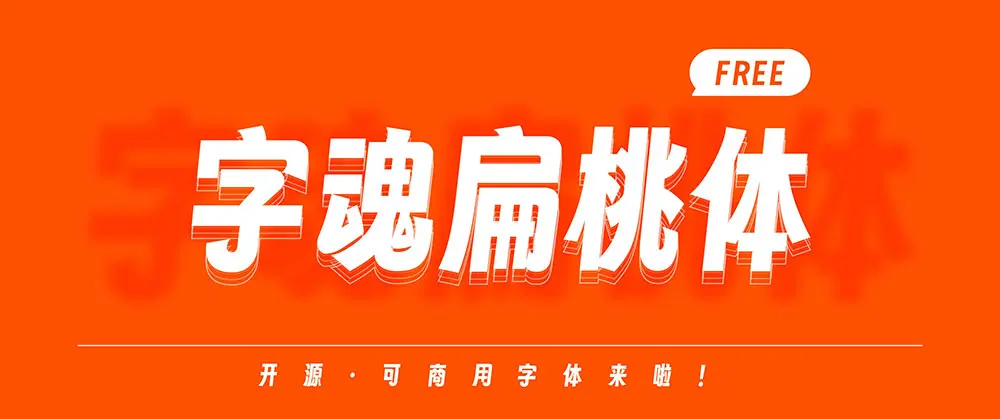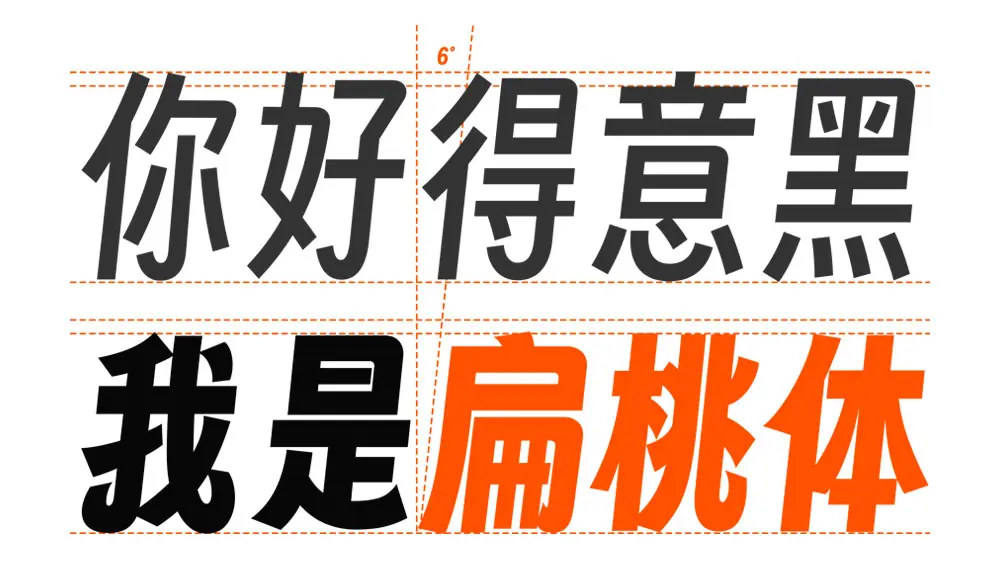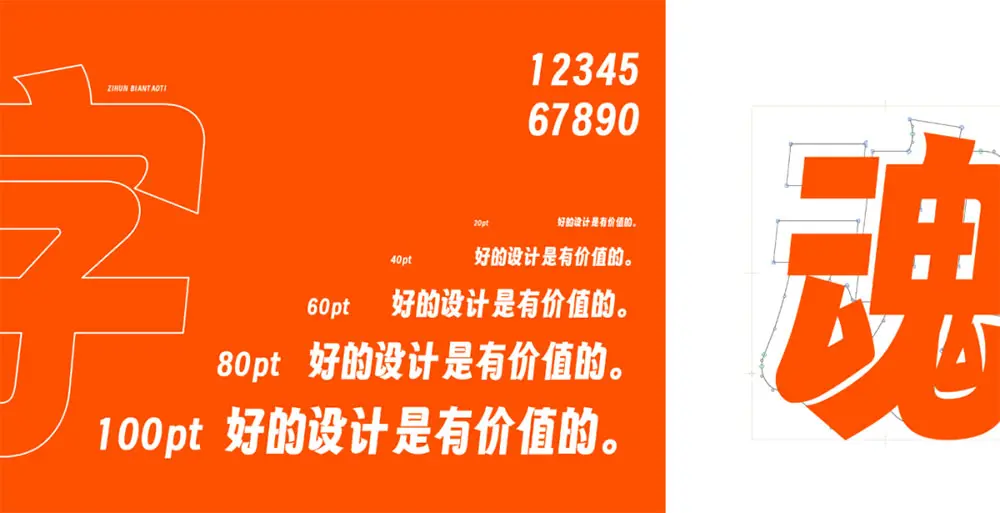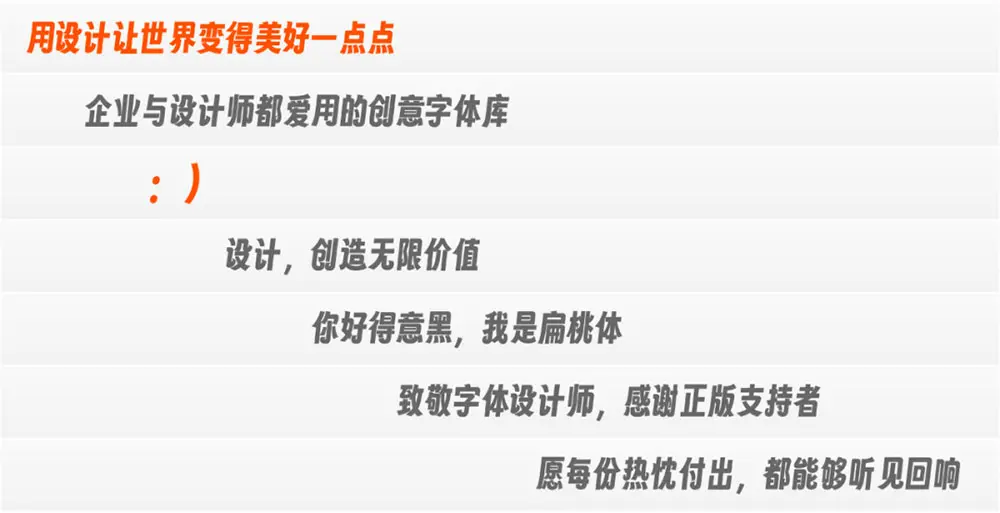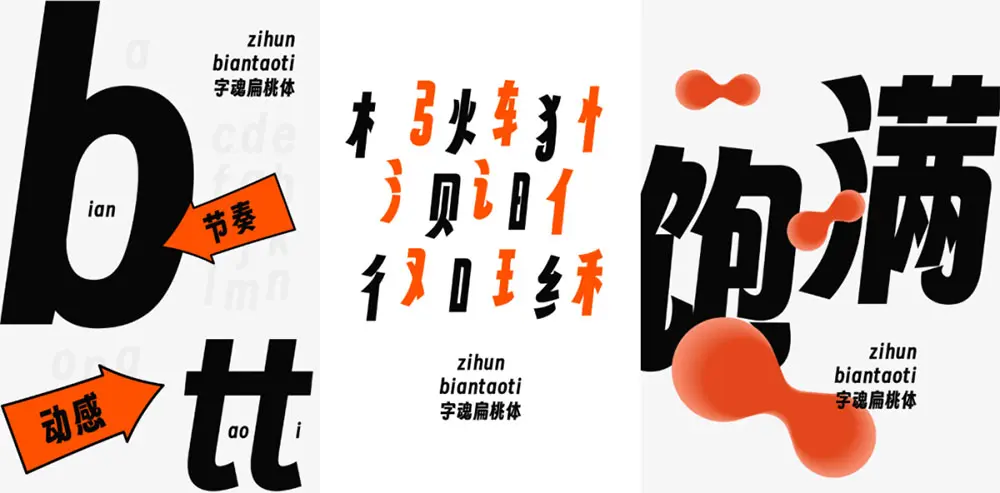
去年,oooooohmygosh老師與錨鎢團隊發佈了免費商用字體「得意黑」。字魂網對得意黑進行二次創作,發佈開源字體「字魂扁桃體」,同樣是開源並永久免費商用,提供給所有用戶。
關於新字體的命名:oooooohmygosh老師在發佈得意黑時,曾提到,歡迎字體設計師們對得意黑進行二創並命名XX體,他開了個玩笑,說叫扁桃體。我們把這款字體做得足夠有趣,也希望用創意讓每個使用者能會心一笑。我們想起了這個“梗”,於是,這套字體,它就叫:「字魂扁桃體」!
這款字體繼承自得意黑標誌性特點:字形6°到8°的傾斜,挺拔高挑,特定筆畫保持彎弧處理。它精神飽滿,溫和又時髦。我們在得意黑基礎上加粗字重,且略微加寬字身,提升整體重量感。特色喇叭口設計讓得意黑的標誌性微笑弧度“捲起來了”。
這個創意讓整個字體充滿活力,個性鮮明。得益於漢字結構豐富,喇叭口小卷產生了無限可能。類似的創意還有很多……,我們不遺餘力地為每個筆畫尋找最適合並有趣的處理方式。這些變化讓字體有了新的功能性,比如在現代媒介、商業宣傳,這些場景能更好適配,因為它更醒目且獨特了。